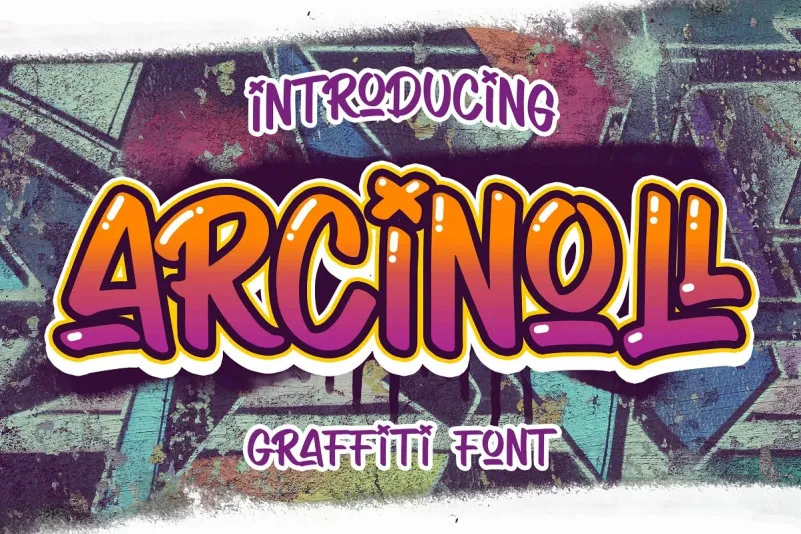
Arcinoll Font
A Arcinoll Font é uma nova fonte criada pela Almarkha Type para atender a demanda crescente por estilo muralista e design infantil. Inspirada no graffiti, ela traz um tema divertido e animado que se destaca perfeitamente em trabalhos como cartazes de graffiti, postais para crianças, flyers promocionais ou capas de livros infantis. Suas linhas dinâmicas e cores vibrantes garantem uma identidade visual forte, ideal tanto para projetos relacionados a personagens infantis quanto para o logo design de marcas divertidas e criativas. Esta fonte é uma escolha inteligente para designers buscando um arretado e único estilo muralista, especialmente para elementos que precisam transmitir leveza e bom humor aos seus projetos. Seja qual seja a sua necessidade de design, a Arcinoll Font certamente oferece um toque especial para qualquer projeto.